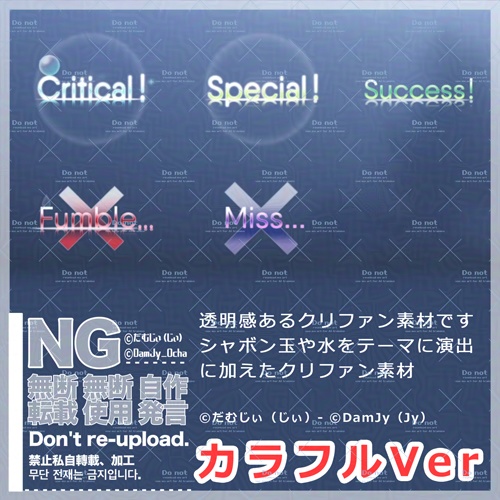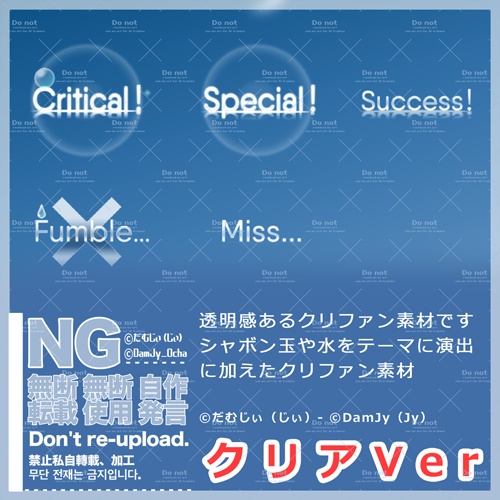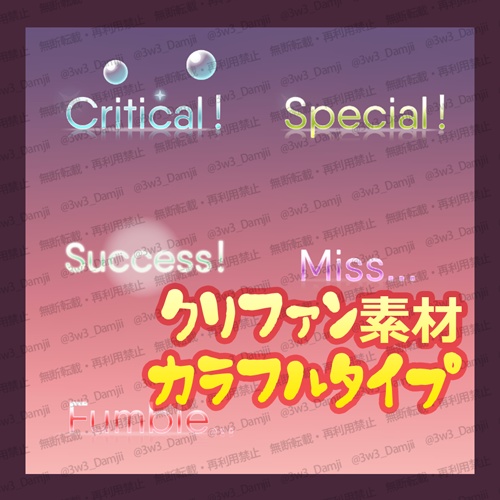
【クトゥルフ6版/インセイン/シノビガミ】クリファン素材(クリア&カラフルVer)水のように透明なフォント✨️
【クトゥルフ6版 / 透明シリーズ】クリファン素材(カラフルVer)APNGセット 薄く着色した半透明のクリファン素材です。
【クトゥルフ6版 / 透明シリーズ】クリファン素材(クリアVer)APNGセット 薄く着色した半透明のクリファン素材です。